¿Por qué la tipografía de la PlayStation 3 es la misma que usó la trilogía de Spider-Man?
¿Te diste cuenta? Si tuviste o tienes la primera PS3, seguro habrás notado que su logo utiliza la misma tipografía que las películas de Spider-Man de Tobey Maguire. Te contamos por qué.
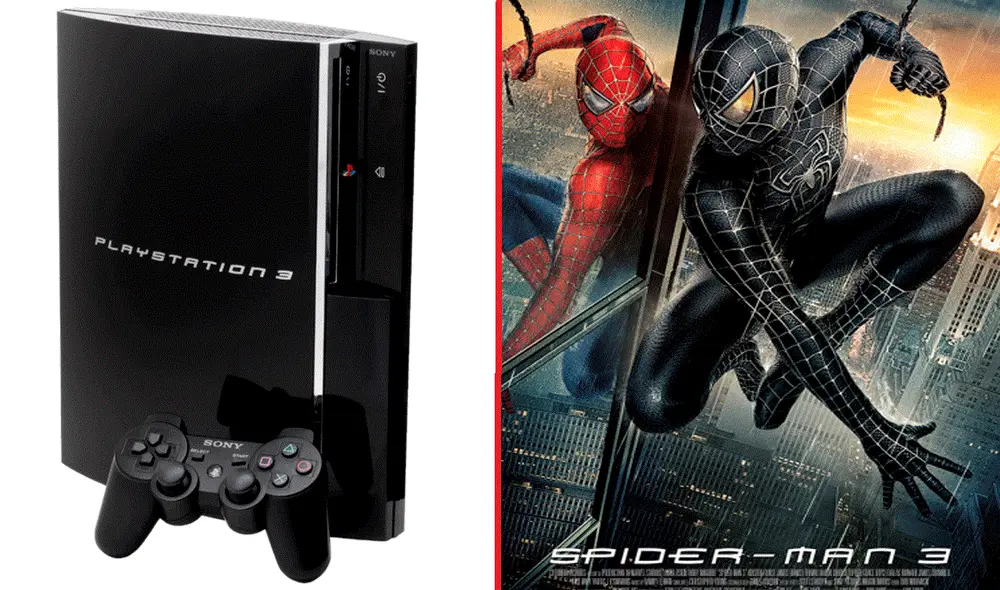
Cuando Sony presentó la primera versión de la PlayStation 3, el 11 de noviembre de 2006, miles de gamers quedaron impresionados. No solo por la calidad de sus gráficos, también por su diseño. Uno de los detalles más curiosos de la consola está relacionado a su tipografía, que era la misma que Sam Raimi utilizó en la trilogía de películas de Spider-Man. ¿Por qué?
¿Por qué la PlayStation 3 usaba la tipografía de Spider-Man?
En aquel entonces, las películas de Spider-Man protagonizadas por Tobey Maguire fueron un éxito en taquilla, llegando a acumular millones de dólares en todo el mundo. Sony quería que su nueva consola de videojuegos tuviera el mismo éxito, así que aprovechó la enorme popularidad del arácnido para crear una conexión visual con la primera PS3 (modelo Fat).
Según detalla 3DJuegos, esta estrategia de Sony no es una teoría elaborada por los fans, ya que el mismo Ken Kutaragi (ex presidente y CEO de Sony Interactive Entertainment) no tuvo problemas en admitir que la tipografía de la PS3 se basó en aprovechar una marca ya reconocida, que formaba parte de la identidad visual de la compañía.
Teiyu Goto, diseñador del control de PlayStation 1, también confirmó que Sony no quería correr riesgos elaborando una tipografía desde cer. Por ese motivo, prefirieron tomar prestada la de Spider-Man, de la cual ya tenían los derechos cinematográficos. “Si se mira la PS3 de perfil, se puede ver que el contorno es redondeado", sostuvo.
De acuerdo a la publicación, la tipografía que Sam Raimi utilzó en Spider-Man (2002), Spider-Man 2 (2004) y Spider-Man 3 (2007) se llama 'Mata' y se caracteriza por sus "formas estilizadas, líneas alargadas y un diseño que refleja dinamismo". Aunque para muchos pueda lucir un poco anticuada, en su momento, expresaba modernidad.
¿Por qué cambiaron la tipografía de la PlayStation 3?
En agosto de 2009, tres años después de lanzar la PlayStation 3 (modelo Fat), Sony presentó la PS3 Slim, una versión más delgada y menos ruidosa que la original. No solo hubo cambios internos, como la eliminación de la retrocompatibilidad con la PS2, también cambios externos como la eliminación de la tipografía inspirada en Spider-Man. ¿Por qué razón?
Quizás no lo recuerdes, pero la PlayStation 3 no fue un éxito instantáneo, como si lo fue la PS1 y PS2, esto debido a varios factores como su elevado precio, la fuerte competencia (Xbox 360) y falta de juegos. Por ese motivo, Sony decidió relanzarla y cambiar la tipografía por un logo más tradicional. Este nuevo diseño se mantuvo también en la PS3 Super Slim, la última versión que llegó en 2012.